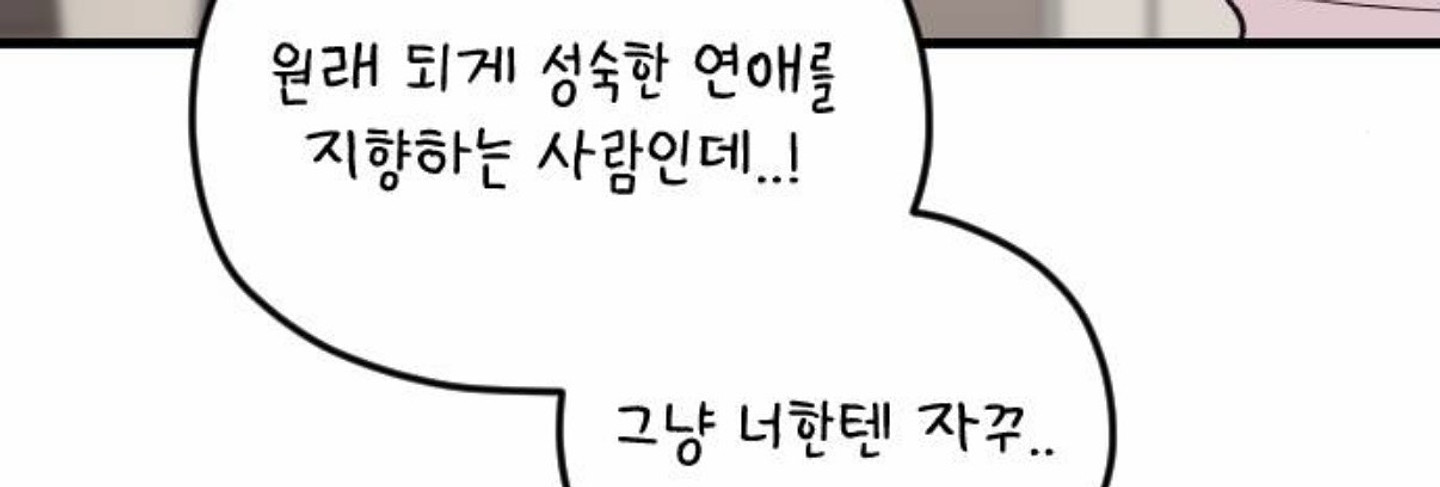
이 폰트 HU하늘고딕 140로 알려주셨는데 느낌은 비슷하지만 히읗이 다르고 사진 속 폰트가 획이 더 긴 느낌이라 정확히 알려주실분 ㅜㅜ
폰트 찾을 수 있을까요? 그냥 인터넷에서 주운 이미지인데.. 괄호가 완전 둥그스름 형태가 아니고 살짝 각이 있는 특징이 있습니다 ㅠㅠ